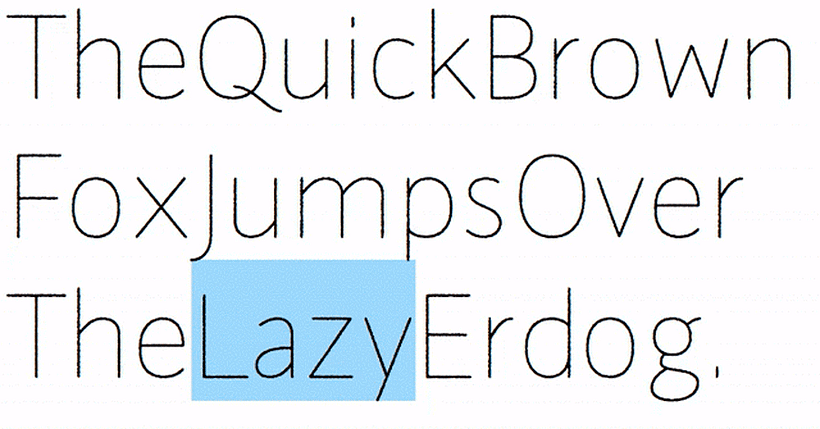
Galata, la tipografía reivindicativa que permite jugar
Su apariencia sencilla esconde varias reivindicaciones políticas y algunos "huevos de pascua" en forma de juegos.
El diseñador y tipógrafo austríaco Rainer Erich Scheichelbauer se encontraba en Estambul en 2013, en un momento de tensión política en el que las protestas contra el presidente Erdoğan se sucedían. En medio del caos, Scheichelbauer decidió salir a conocer la realidad y entre manifestantes y gases lacrimógenos se refugió en un callejón en el que leyó un grafiti en el que se leía "Erdogone" (un juego de palabras entre el nombre del presidente y la palabra "gone": acabado) y ese fue el germen para crear Galata, una tipografía creada con Inteligencia Artificial que, además de lanzar un mensaje político, esconde tres juegos.
La tipografía Galata reconoce cuando tratamos de teclear la palabra Erdoğan y la reemplaza inmediatamente por "Erdogone". Algo similar ocurre cuando escribimos 'Gezi' –el nombre del parque turco en el que comenzaron las protestas–; las letras que rodean la palabra se hacen a un lado para dejar más espacio a ese pequeño espacio que ha cobrado tanta importancia y que ha dado nombre a las protestas de 2013.
Galata esconde también tres juegos que permiten al usuario interactuar con la tipografía. Con solo teclear un sencillo comando ('###' para el tres en raya, por ejemplo) la tipografía nos devuelve una secuencia que nos permite retar a Galata. Esta fuente tipográfica, disponible en más 203 idiomas, también esconde un 'piedra, papel o tijeras' y el 'Nim' o 'Marienbad'.
La tipografía Galata, bautizada como uno de los barrios de Estambul, explora las posibilidades de la tipografía aplicada a la Inteligencia Artificial.